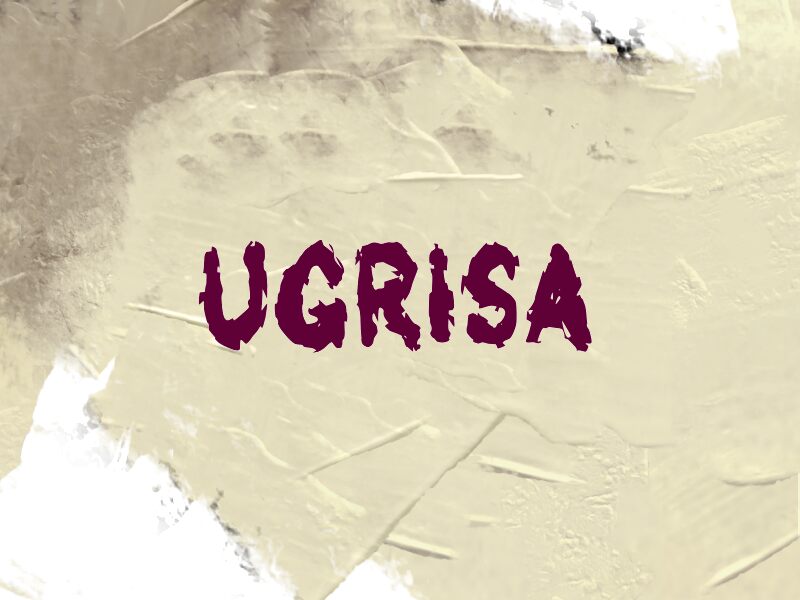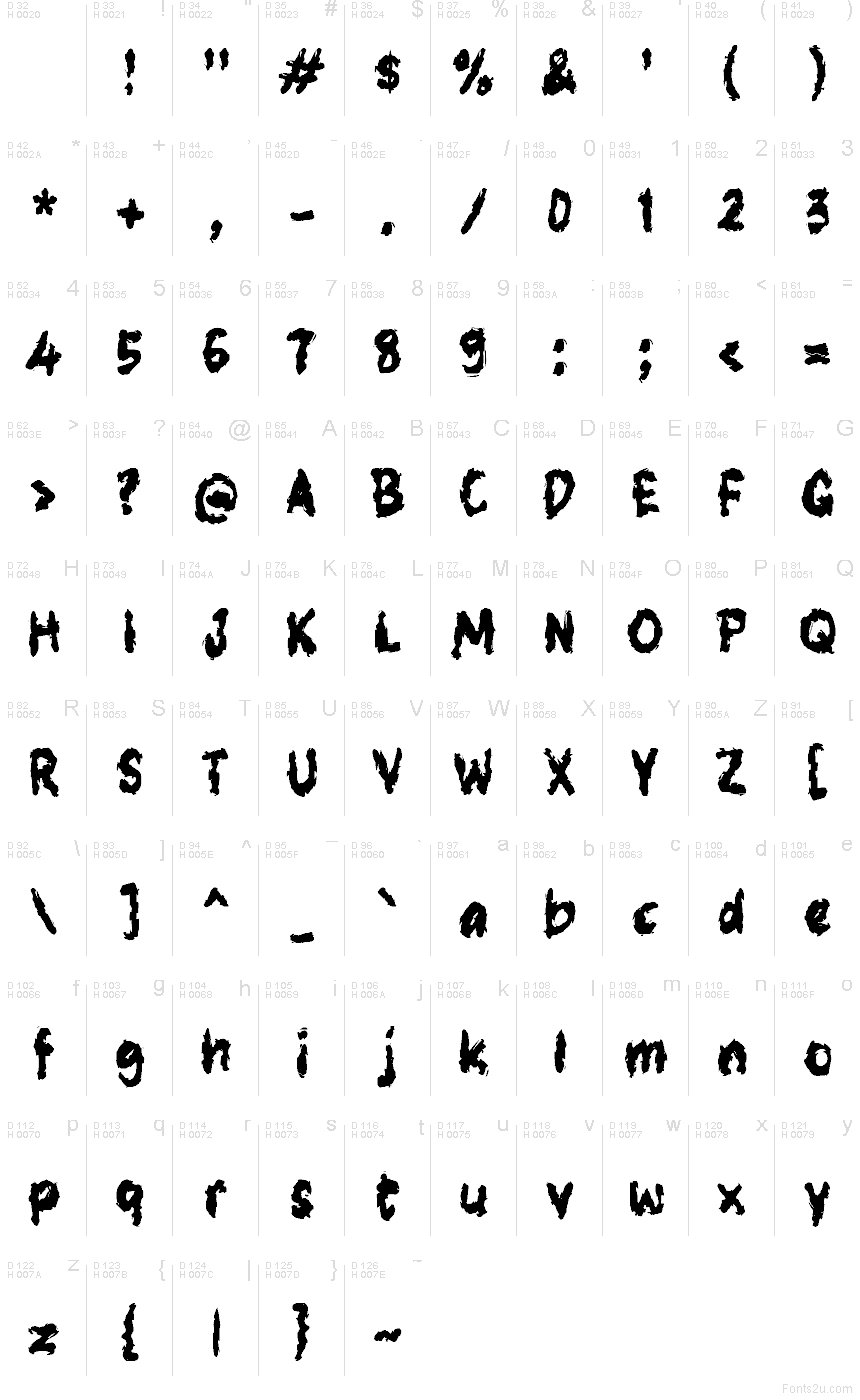
Ugrisa di Wep è un font brush in stile trash, grezzo e con un'attitudine "strappata a mano". Le lettere sembrano ricavate da vernice densa o carta stracciata, con bordi smussati, pesi irregolari e spazi vuoti che rendono l'intero set rumoroso, nervoso e un po' selvaggio.
È perfetto per flyer musicali, poster horror, grafiche streetwear, copertine di fanzine e titoli dove una geometria pulita risulterebbe troppo formale. Come font gratuito, UGRISA dà il meglio di sé in contesti brevi e di impatto come nomi di band, titoli di eventi, slogan di protesta o monogrammi grezzi, perché la silhouette maltrattata comunica forza prima ancora di ogni dettaglio.
Ugrisa